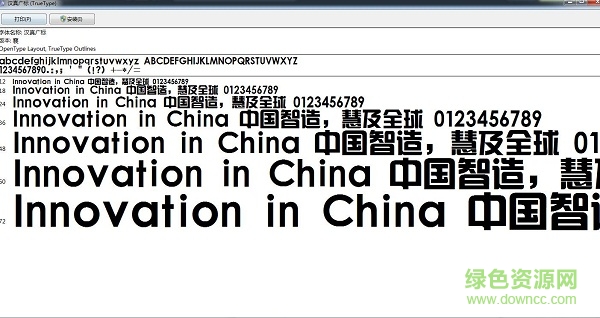
軟件介紹 軟件標簽: hzgb字體 字體 hzgb是什么字體?hzgb字體就是漢真廣標字體,這款字體弧線過渡平穩(wěn),圓弧漂亮,筆畫對稱,大方莊重,適合用作大字標題或是產(chǎn)品包裝設(shè)計。,需要的朋友歡迎在綠色資源網(wǎng)免費下載!常用字體特征【黑體】:筆畫簡潔平直,無邊角修飾。【宋體】:筆畫有較多的邊角修飾。【書法體】:將文字以美感和圖案的方式進行表達。優(yōu)秀字體推薦hyrunyuan-cew字體 授權(quán):免費軟件 WinAll大?。?.5M語言:中文hyrunyuan-cew是什么字體?hyrunyuancew是一款漢儀潤圓35wthin字體,該字體具有鮮明的節(jié)奏感,簡潔規(guī)整,便于識別,給人一種爽朗的感受,需要的小伙伴快來下載吧!hyrunyuan相關(guān)字體推薦字體設(shè)計原則1.文字的設(shè)下載地址hyy2gf 授權(quán):免費軟件 WinAll, WinXP, Win7, Win8大?。?.9M語言:中文hyy2gf字體就是漢儀蘿卜體,該字體字如其名,就像蘿卜一樣上面粗下面細,天真浪漫又萌又酷,可用作兒童主題的海報和讀物設(shè)計或是裝飾字體,喜歡美術(shù)字體的朋友快來下載吧!裝飾字體介紹裝飾字體是在基本字形的基礎(chǔ)進下載地址hzgb字體安裝方法方法一:直接將字體復制到C:\WINDOWS\Fonts;方法二:控制面板/字體/文件/安裝新字體;方法三:針對win7系統(tǒng),用戶只需選中字體右鍵安裝即可。 軟件截圖 上一張下一張(1 / 1) 安裝詳細截圖 其他版本下載 標題 大小 更新日期 下載 下載地址 電腦版 hzgb regular免費字體 點擊報錯 軟件無法下載或下載后無法使用,請點擊報錯,謝謝! 關(guān)閉報錯反饋 請描述您所遇到的錯誤,我們將盡快予以修正,謝謝! *必填項,請輸入內(nèi)容 本類最新 dreamweaver字體庫 首爾南山體字體 v1.06 官方版 潮字社風云簡ttf 潮字社凌渡鯤鵬簡體字體 潮字社曾玉波手書簡字體 微博慧心字體 相關(guān)文章 Photoshop字體安裝使用方法和技巧 如何解決“無法新增字體”問題 Win 7系統(tǒng)安裝字體方法 網(wǎng)頁字體大小設(shè)置方法 怎么改網(wǎng)頁字體大小 在Linux系統(tǒng)中安裝字體的幾種方法 windows7字體顯示問題:打開某些程序的時候顯示的是亂碼 用戶評論 熱門評論 最新評論 發(fā)表評論 查看所有評論(0) 昵稱: 請不要評論無意義或臟話,我們所有評論會有人工審核. 字數(shù): 0/500 (您的評論需要經(jīng)過審核才能顯示)